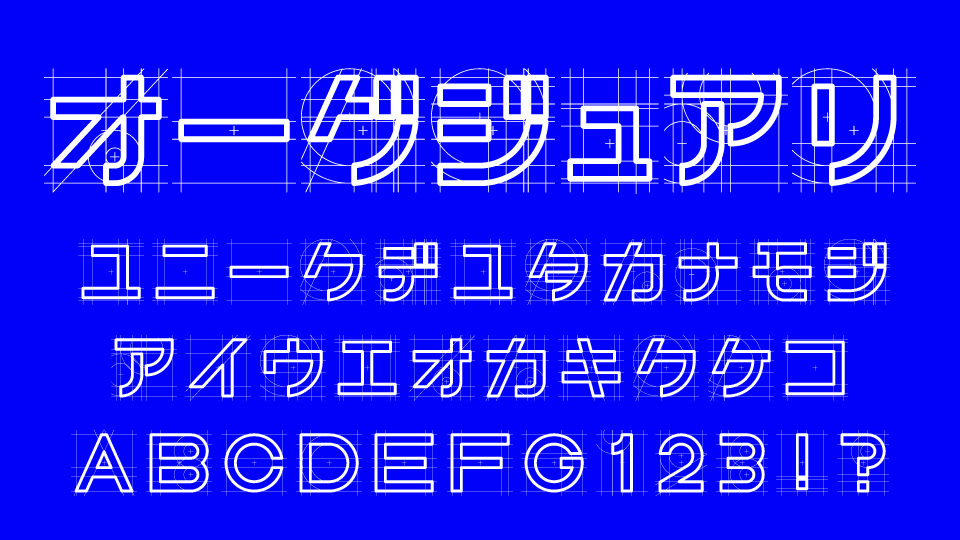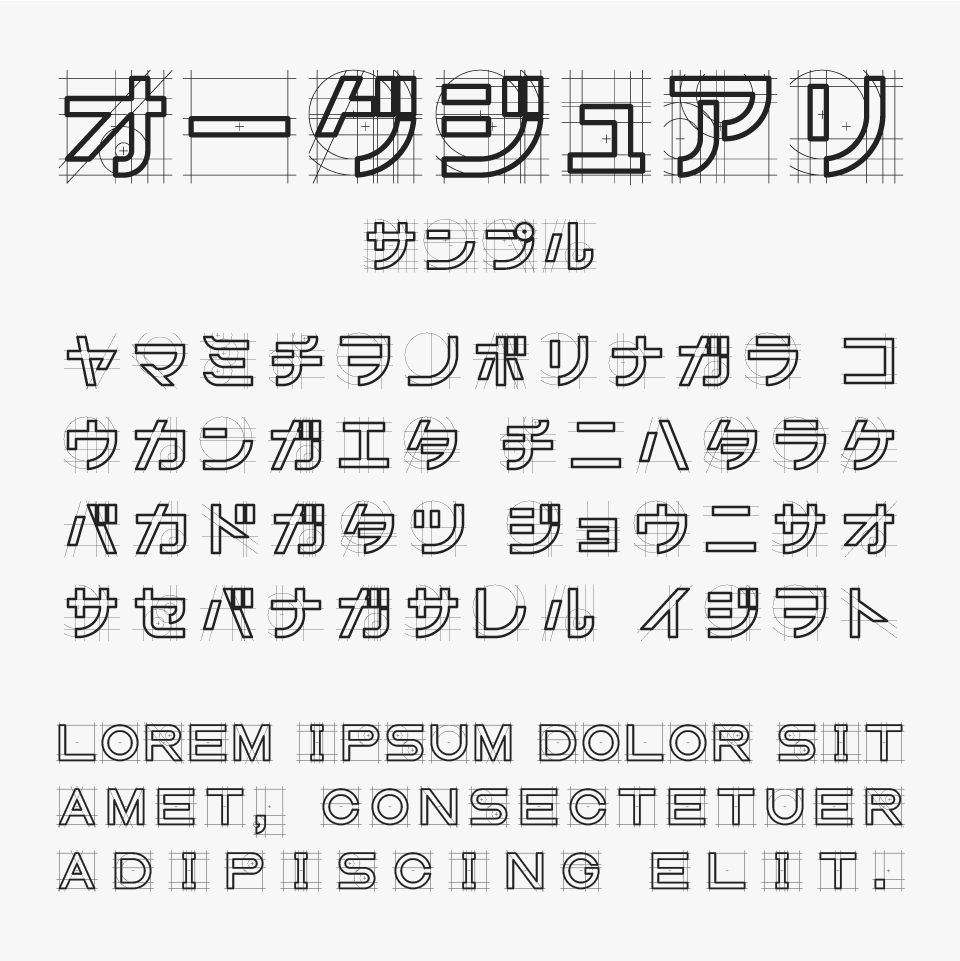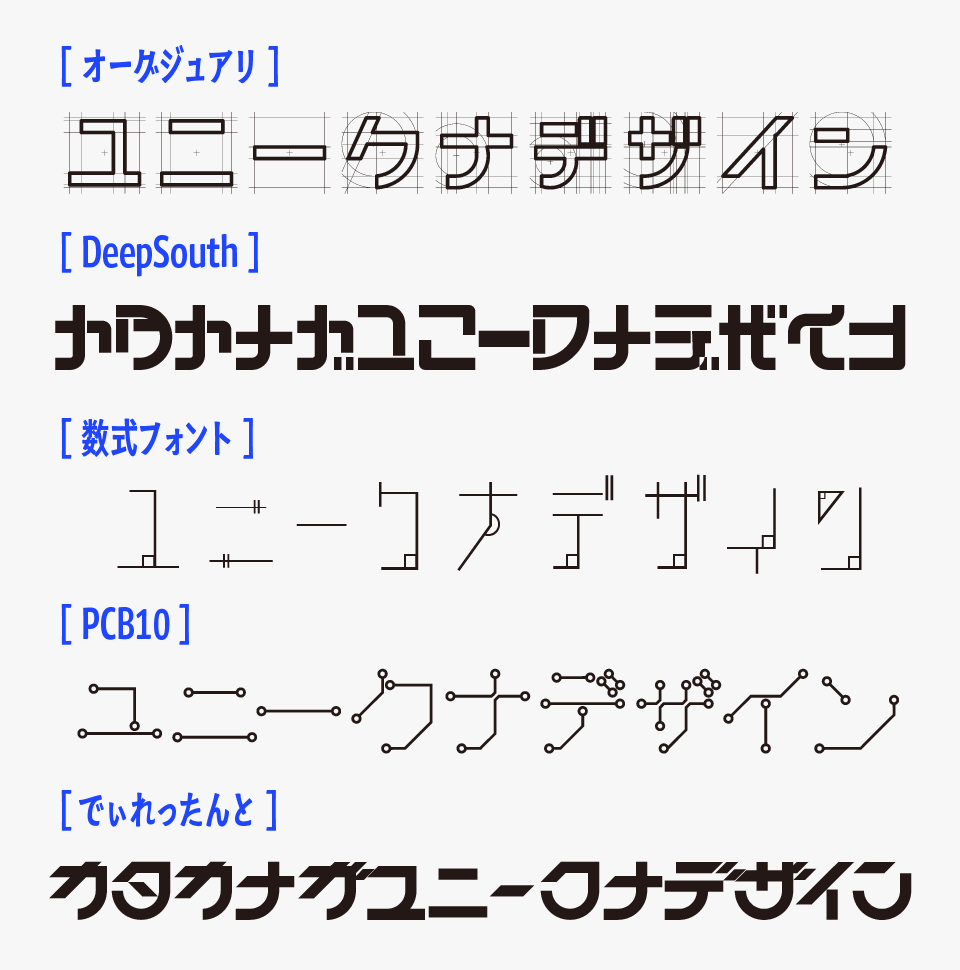
Auxiliary line (オーグジュアリライン)
オーグジュアリフォントは、設計図や製図で使われるガイドラインや補助線をそのままデザインへ取り入れた、ユニークなコンセプトのデザインフォントです。
制作途中かな?と思わせるラフな線が重なることで、完成品と設計過程を同時に見せるような独特の遊びココロが詰まったフォントです。ベースは無機質で知的な雰囲気がありながら、クリエイティブな遊び心も感じられるフォントです。
建築やプロダクトデザイン、UI・UX、テクノロジー、プレゼン資料、ポートフォリオなど、ものづくりをテーマにしたデザインにぴったりなフォントです。設計や試行錯誤そのものをデザインとして表現できるため、クリエイターらしい世界観を演出したい場面で活躍してくれます。
オーグジュアリフォントを、ほかのコンセプト性の高いデザインフォントと比較してみると、設計図そのものをモチーフにした独創的な表現が特徴のフォントとなっています。
収録文字は、カタカナ・アルファベット・数字・記号が収録されています。